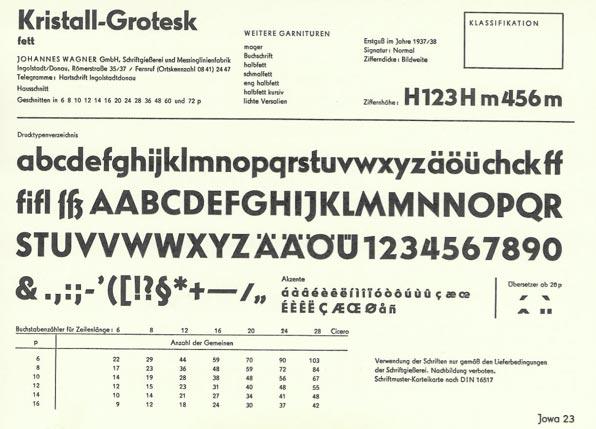
Kristall-Grotesk / bzw. Rund-Grotesk
Seit kurzem gibt es einen Digitalsatz von der alten Kristall-Grotesk, auch Rundgrotesk genannt.
Man kann sogar die mittelfette Garnitur frei herunterladen. Ich habe es getan.
Aber: Die ganzen Unterlängen sind abgeschnitten. Man kann also die Schrift nicht gebrauchen.
Schade ist, dass das "ß" modernisiert wurde und nicht mehr wie das ursprüngliche "sz" aussieht.
Seltsamerweise gibt es aber dennoch eine Version mit dem richtigen "ß". Weiß jemand, wie das zusammenhängt?
Ich finde diese Grotesk wegen ihres runden "b" und in die Unterlänge gezogenenes "f" so wunderschön!
Seltsamerweise gibt es aber dennoch eine Version mit dem richtigen "ß".
Nicht seltsam, sondern Opentype, siehe http://rundgrotesk.de/content/Rund-Grotesk-OpenType-features.pdf
Das mit den Unterlängen habe ich (noch) nicht getestet.